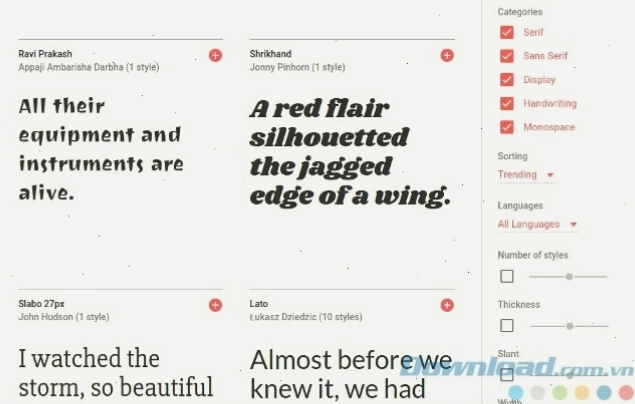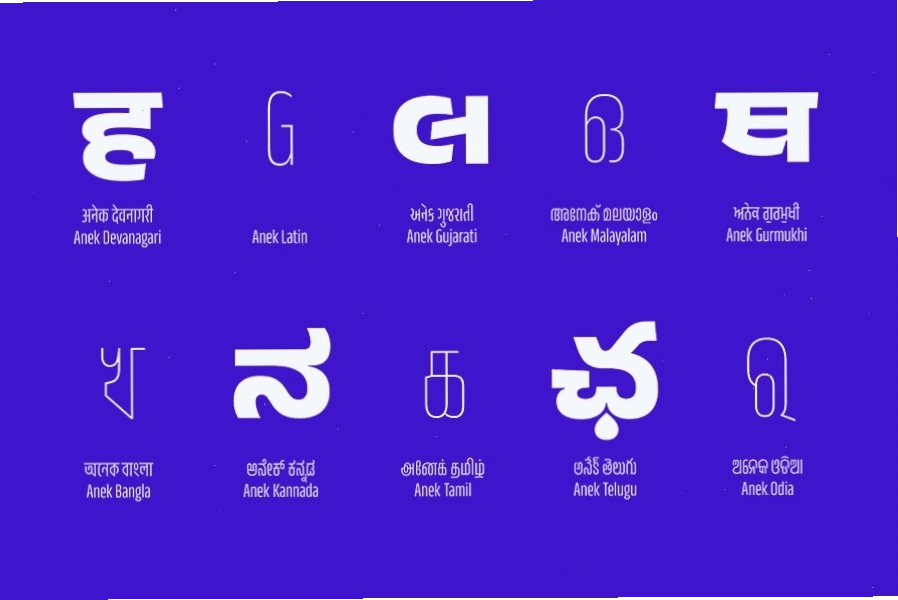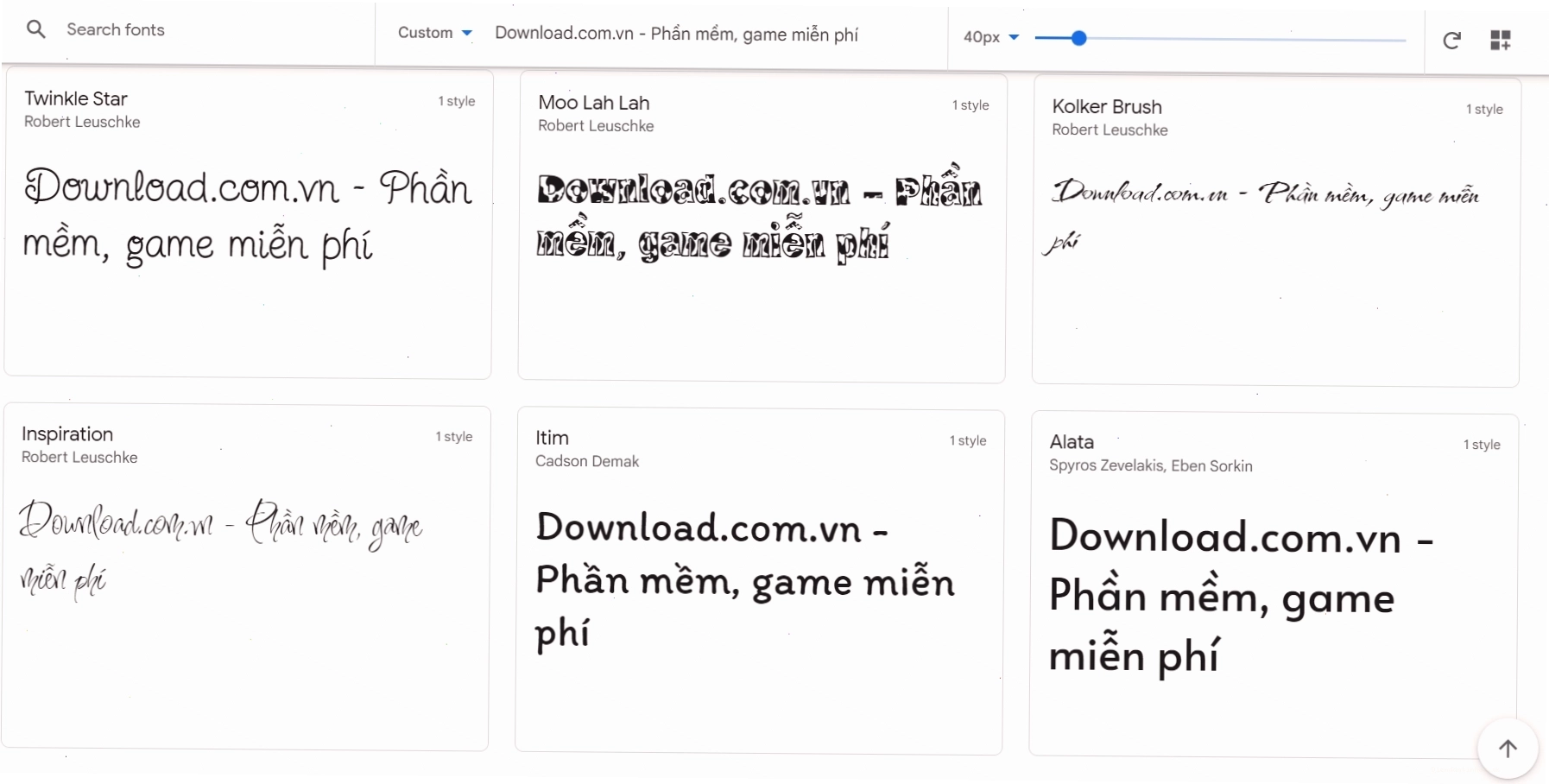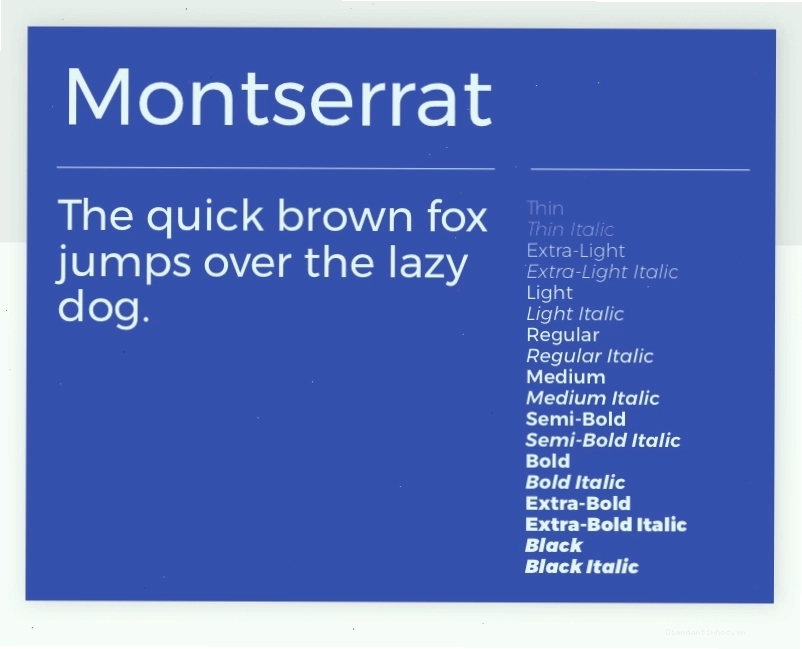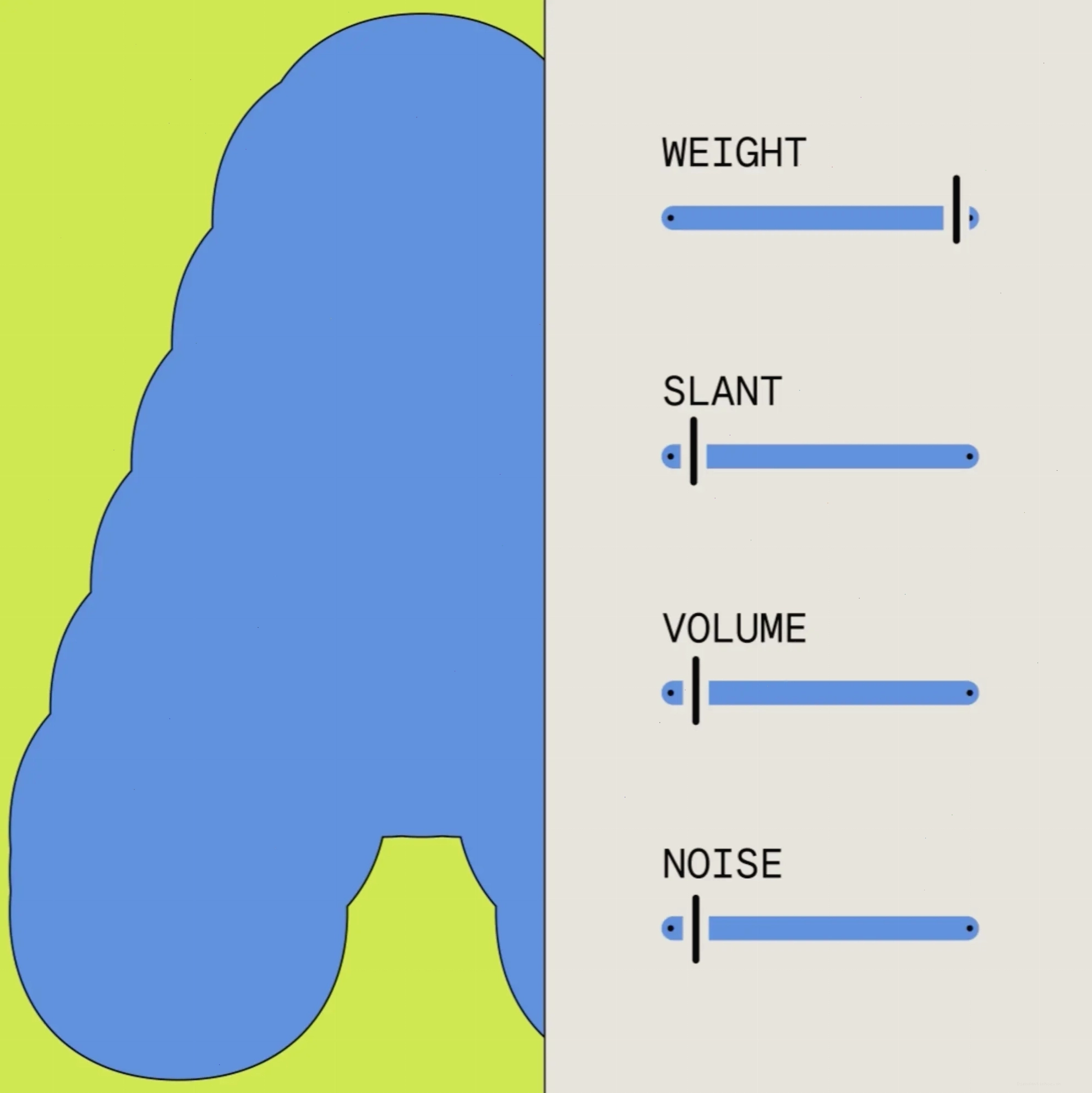
Tầm quan trọng của font chữ trong thiết kế website
Trong kỷ nguyên số hóa, website không chỉ đơn thuần là nơi cung cấp thông tin mà còn là bộ mặt đại diện cho thương hiệu, doanh nghiệp. Một thiết kế website ấn tượng, chuyên nghiệp sẽ thu hút và giữ chân người dùng hiệu quả. Trong đó, việc lựa chọn font chữ phù hợp đóng vai trò then chốt, ảnh hưởng trực tiếp đến trải nghiệm thị giác, khả năng đọc hiểu và cả thông điệp mà bạn muốn truyền tải.
Google Fonts, với kho tàng font chữ đồ sộ, miễn phí và mã nguồn mở, đã trở thành giải pháp tối ưu cho các nhà thiết kế, lập trình viên và chủ sở hữu website. Bộ sưu tập này không chỉ cung cấp sự đa dạng về phong cách mà còn đảm bảo tính tương thích cao trên mọi thiết bị và trình duyệt.
Google Fonts là gì và tại sao nên sử dụng?
Google Fonts là dịch vụ cung cấp miễn phí hàng ngàn bộ font chữ chất lượng cao, có thể sử dụng trực tiếp trên website hoặc tải về để cài đặt trên máy tính. Ra đời với mục tiêu dân chủ hóa thiết kế, Google Fonts giúp mọi người tiếp cận và sử dụng các font chữ chuyên nghiệp mà không tốn chi phí bản quyền.
- Miễn phí và mã nguồn mở: Sử dụng không giới hạn cho mọi dự án cá nhân và thương mại.
- Đa dạng ngôn ngữ: Hỗ trợ hơn 135 ngôn ngữ, bao gồm cả tiếng Việt, giúp tiếp cận đa dạng đối tượng người dùng.
- Tối ưu hiệu suất web: Font chữ được nén bằng công nghệ WOFF 2.0, giúp website tải nhanh hơn, đặc biệt trên các kết nối mạng yếu.
- Dễ dàng nhúng và tùy chỉnh: Cung cấp mã nhúng đơn giản hoặc tùy chọn tải về để sử dụng ngoại tuyến.
- Cập nhật liên tục: Luôn có những font chữ mới, đáp ứng xu hướng thiết kế.
Khám phá thế giới font chữ Google đa dạng và phong phú
Với hơn 1.400 gia đình font chữ và ngày càng tăng, Google Fonts đáp ứng mọi nhu cầu thiết kế, từ trang trọng, chuyên nghiệp đến trẻ trung, sáng tạo. Dù bạn đang tìm kiếm một font chữ cho tiêu đề, nội dung chính, hay thậm chí là các yếu tố đồ họa nhỏ, Google Fonts đều có thể đáp ứng.
Các danh mục font chữ phổ biến
Google Fonts phân loại font chữ theo nhiều tiêu chí, giúp người dùng dễ dàng tìm kiếm và lựa chọn:
- Serif: Các font có chân, mang lại cảm giác truyền thống, trang trọng và dễ đọc cho các đoạn văn bản dài. Ví dụ: Merriweather, Alegreya.
- Sans Serif: Các font không chân, hiện đại, sạch sẽ và rõ ràng, thường được ưa chuộng cho tiêu đề và nội dung trên web. Ví dụ: Inter, Roboto, Open Sans.
- Display: Các font độc đáo, mang tính nghệ thuật cao, thường dùng cho các tiêu đề lớn, logo hoặc các yếu tố nhấn mạnh. Ví dụ: Anton, Bangers.
- Handwriting: Các font mô phỏng chữ viết tay, tạo cảm giác cá nhân, thân thiện. Ví dụ: Alex Brush, Amatic SC.
- Monospace: Các font có khoảng cách ký tự cố định, thường thấy trong code hoặc các ứng dụng yêu cầu sự căn chỉnh chính xác. Ví dụ: Source Code Pro.
Google Font tiếng Việt và các biến thể
Nỗi lo về việc thiếu font chữ tiếng Việt chuẩn xác và đẹp mắt đã được giải quyết với Google Fonts. Nhiều font chữ tại đây hỗ trợ đầy đủ bảng mã tiếng Việt, bao gồm cả các dấu thanh và ký tự đặc biệt. Các font như Inter, Roboto, Open Sans, Lora, Noto Serif, Noto Sans... đều là những lựa chọn tuyệt vời cho website tiếng Việt, đảm bảo tính thẩm mỹ và dễ đọc.
Ngoài ra, Google còn cung cấp các font chữ biến thể (variable fonts) như Google Sans Flex, cho phép tùy chỉnh linh hoạt các thuộc tính như độ dày, độ nghiêng, khoảng cách ký tự, mang đến khả năng sáng tạo không giới hạn cho nhà thiết kế.
Tối ưu hóa hiệu suất website với Google Fonts
Một trong những ưu điểm vượt trội của Google Fonts là khả năng tối ưu hóa tốc độ tải trang. Khi bạn nhúng một font chữ từ Google Fonts vào website, Google sẽ tự động gửi phiên bản font có kích thước nhỏ nhất, phù hợp với trình duyệt và thiết bị của người dùng, nhờ vào công nghệ nén dữ liệu WOFF 2.0.
Điều này không chỉ cải thiện trải nghiệm người dùng, đặc biệt là trên các kết nối mạng chậm, mà còn góp phần tăng thứ hạng SEO cho website của bạn. Tốc độ tải trang nhanh là một yếu tố quan trọng được Google đánh giá cao.
Cách nhúng và sử dụng Google Fonts cho website
Việc tích hợp Google Fonts vào website vô cùng đơn giản, bạn có thể lựa chọn một trong hai phương pháp chính:
1. Sử dụng thẻ link (HTML)
Bạn cũng có thể thêm đoạn mã `@import` vào file CSS của mình. Tuy nhiên, phương pháp sử dụng thẻ `` thường được khuyến khích hơn vì nó có thể tối ưu hóa việc tải font song song.
Google Fonts là một nguồn tài nguyên vô giá, giúp nâng tầm thiết kế website của bạn mà không tốn kém. Bằng việc lựa chọn và sử dụng font chữ một cách thông minh, bạn không chỉ tạo ra một giao diện đẹp mắt, chuyên nghiệp mà còn tối ưu hóa trải nghiệm người dùng và hiệu suất hoạt động của trang web.
Đừng ngần ngại khám phá thư viện đồ sộ của Google Fonts, thử nghiệm với các phong cách khác nhau và tìm ra những font chữ ưng ý nhất cho dự án của bạn. Hãy biến website của bạn trở nên nổi bật và ghi dấu ấn mạnh mẽ trong lòng người truy cập ngay hôm nay!